En unostiposduros hemos recibido multitud de correos solicitándonos información sobre la creación de tipografías digitales. Así hemos podido constatar que la documentación disponible en castellano sobre este tema es realmente escasa. Es por esto, que hemos decidido incorporar a los contenidos de este sitio un curso práctico de creación de tipografías en la confianza de que será de interés para todos vosotros.
En el mismo, pretendemos aunar la teoría y la práctica ya que pensamos que tan importante como saber manejar el programa con el que vamos a crear nuestras tipografías, es conocer los puntos claves en los que se sustenta un buen diseño tipográfico, sobre todo en aspectos cruciales como pueden ser la legibilidad, el correcto espaciado o las proporciones de los caracteres.
Para los contenidos del presente taller hemos recurrido a diversas fuentes: por un lado a los capítulos más interesantes del libro de Sthepen Moye Fontographer type by design, que desgraciadamente ha dejado de editarse, y por otro a los textos que sobre conceptos básicos y efectos ópticos han publicado en sus páginas el colectivo de diseñadores tipográficos Underware y el tipógrafo islandés Gunnlaugur SE Briem a los que agradecemos desde aquí el permiso para reproducir sus trabajos. A estos contenidos y, en los puntos que hemos creído conveniente, hemos añadido por nuestra parte más información que complementa a la ya existente.
Los dos programas mas utilizados para la creación de tipografías digitales son Fontographer (en la actualidad comprado por Fontlab) y FontLab; este tutorial está basado en el primero pero en general las instrucciones y consejos sobre el dibujo de los caracteres sirve para ambos ya que utilizan las curvas Bézier, en las que se basa el lenguaje PostScript, para este fin.
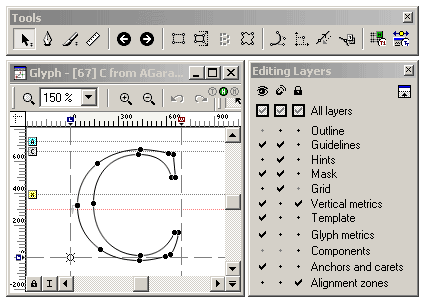
Figura 1 . Ventana del programa Fontlab
Asimismo os recordamos que el dibujo de los caracteres lo podéis realizar con cualquier programa de dibujo vectorial como pueden ser Freehand e Ilustrator para después pasarlos a Fontographer y acabar de realizar la fuente con este programa. (Este método es el preferido por nosotros). En este artículo puedes ver la manera de efectuar el traslado de los caracteres de Freehand a Ilustrator.
6 El correcto espaciado de las letras
El diseño de tipografías es un trabajo meticuloso y en ciertas fases hasta tedioso y repetitivo. Evidentemente este manual proporciona una visión general de una forma de acercase al diseño de tipos en su parte más «mecánica», pero existe otro componente en el diseño de tipos que es el estudio de su historia, sus diferentes tipologias, variaciones, etc, dentro de un determinado contexto y unas circunstancias concretas.
La información que nos proporcionan los referentes historicos de la tipografía es básica para afrontar la creación de tipos en la era digital.